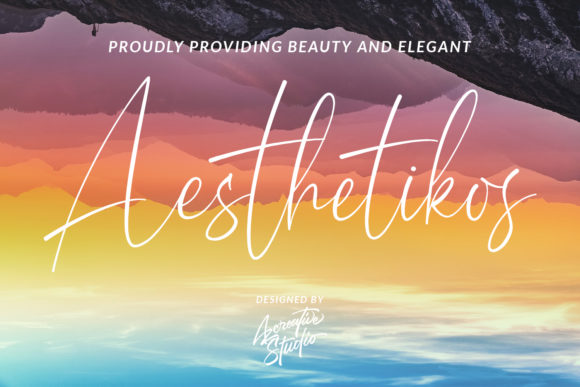
Creativefabrica Aesthetikos Font 2021
[Creativefabrica] Aesthetikos Font (2021)
Aesthetikos кажется невероятно элегантным и плавным.
Он потрясающе смотрится на свадебных приглашениях, благодарственных открытках, цитатах, поздравительных открытках, логотипах, визитных карточках и любом другом дизайне, который нуждается в рукописном штрихе. Он имеет изменяющуюся базовую линию, плавные линии, великолепные глифы и потрясающие чередования.